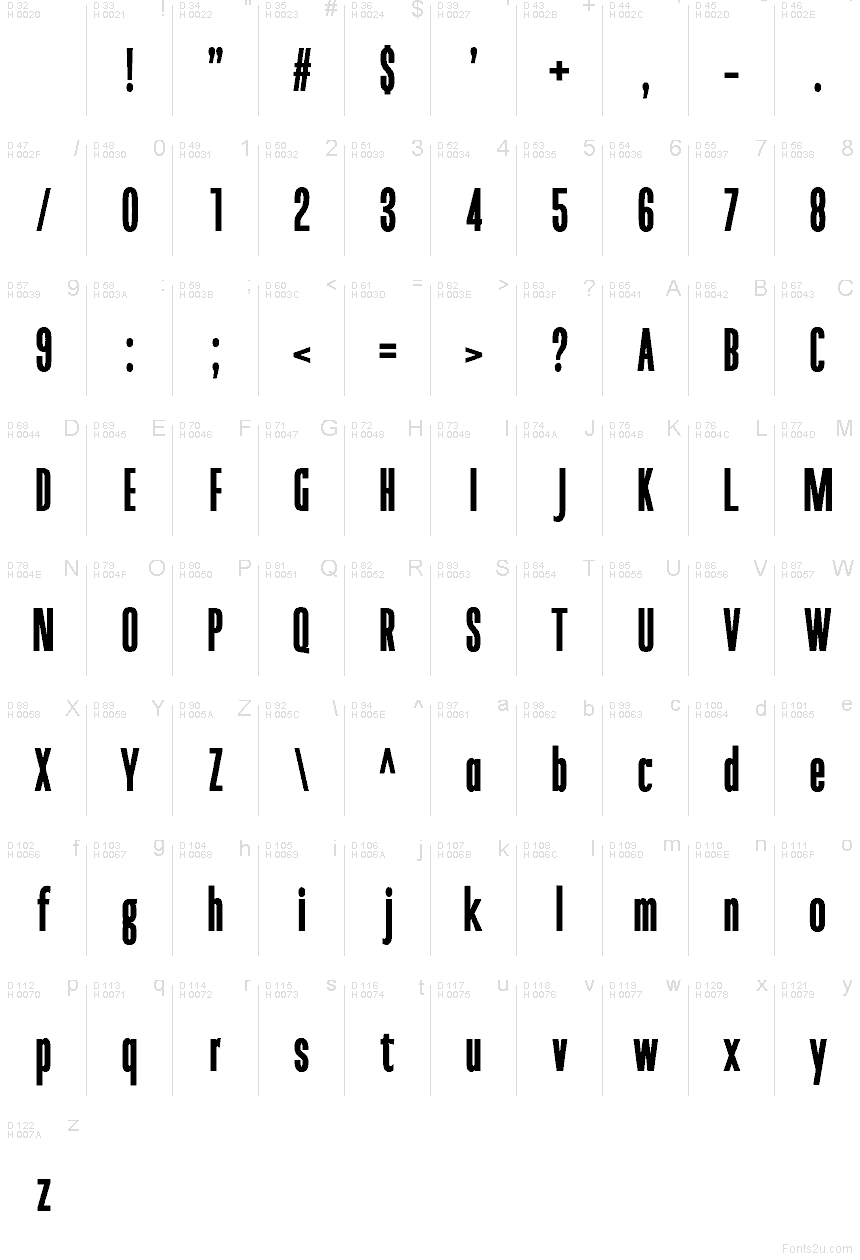
Kopile Bold Condensed d'Afkari Studio est une police sans empattement condensée gratuite au rendu percutant, idéal pour les affiches. Les lettres sont étroitement serrées dans un cadre étroit, utilisant des traits verticaux épais et des formes arrondies simples pour donner à la police un aspect direct, élancé et légèrement urgent.
Elle convient parfaitement au branding, aux flyers musicaux, aux graphismes sportifs, au packaging et aux titres de magazines où l'espace est restreint mais où le message doit avoir du punch. En tant que police gratuite, elle s'adapte aussi aux cartons de titre, aux courts en-têtes web et aux logos superposés, car son rythme compressé garde les lignes compactes sans perdre son caractère affirmé.